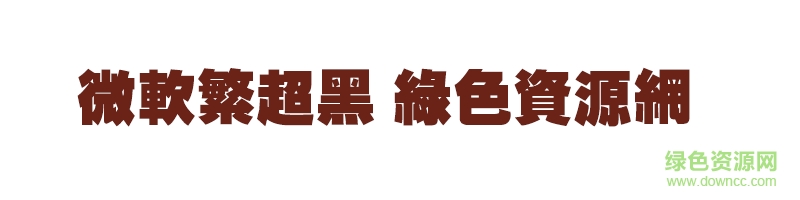
微軟繁超黑是一款繁體的黑體字體,筆畫超粗,看上去非常的醒目,非常適用于各種宣傳頁面,如果有需要經(jīng)常用到藝術(shù)字體的朋友可以來綠色資源網(wǎng)下載體驗哦!
微軟繁超黑結(jié)體疏朗簡潔、工整端莊,筆觸圓潤、粗細(xì)均勻,風(fēng)格簡約流暢、剛?cè)岵?jì)。此款字體適用于兒童讀物、報刊雜志標(biāo)題、廣告設(shè)計等應(yīng)用。